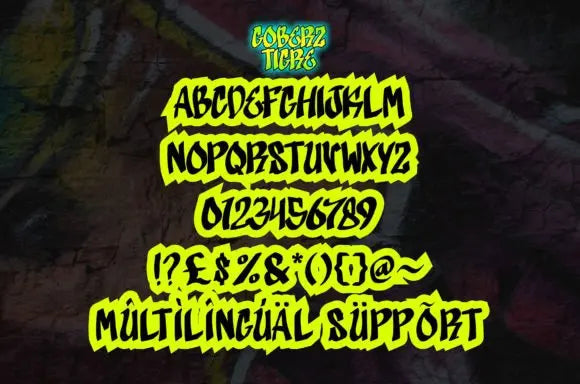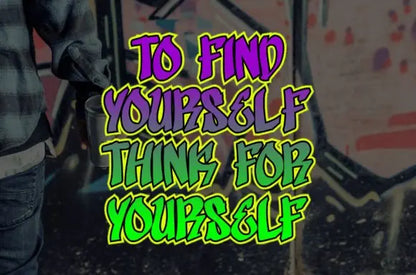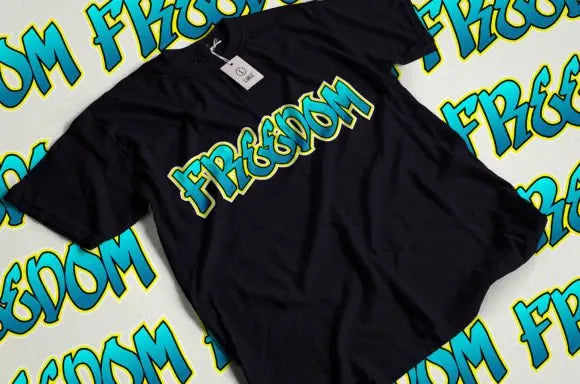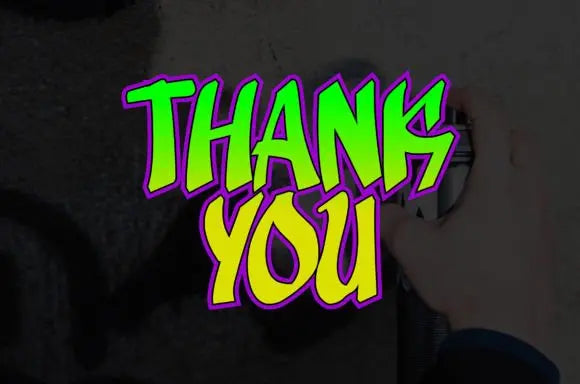
Fuente Goberz Tigre
Goberz Tigre es una fuente de graffiti atrevida y llamativa que es perfecta para hacer una declaración con tus diseños. Esta fuente presenta líneas vanguardistas, formas dinámicas y una sensación urbana contemporánea que elevará cualquier proyecto. Ideal para ropa urbana, música, arte y más, esta fuente seguramente agregará un toque de estilo rebelde a tu trabajo.
Experimente el ambiente vanguardista y contemporáneo con la fuente Goberz Tigre, perfecta para música, ropa urbana, arte y más.
Con líneas atrevidas y formas dinámicas, esta fuente de graffiti elevará cualquier proyecto y agregará un toque de estilo rebelde.